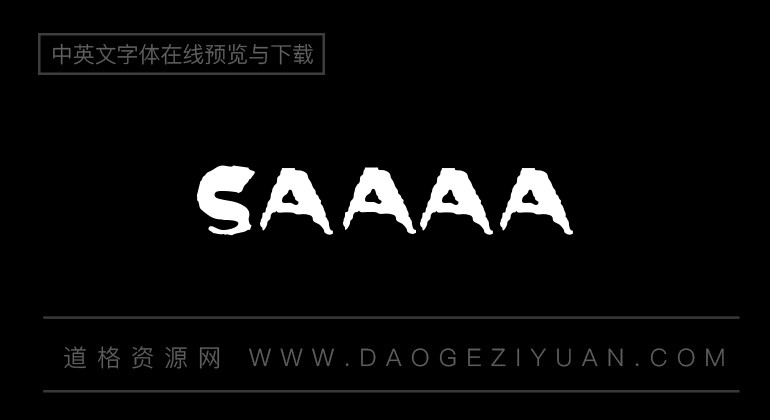
Scary
吧! Scary字体是一种可怕的、恐怖的、可爱的字体,它具有折叠、拉伸、拉长和收缩的特性,可以使文字看起来更加可怕、恐怖、有趣、活泼。Scary字体的设计灵感来自于恐怖电影的海报,它的字体设计充满了恐怖气息,适合用于恐怖电影、游戏、动画等领域的文字表现。
Scary是一款非常不错的手写艺术字体,具有很好的视觉感,适合于文化类的宣传设计、商业类品牌的广告和产品包装设计以及个性化文字排版等较多场景。